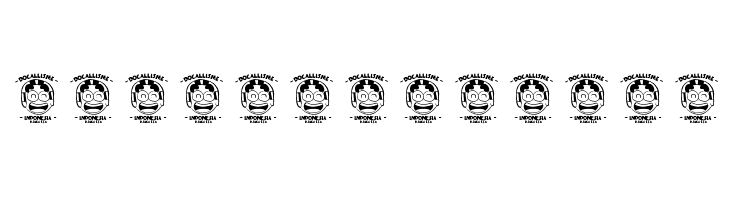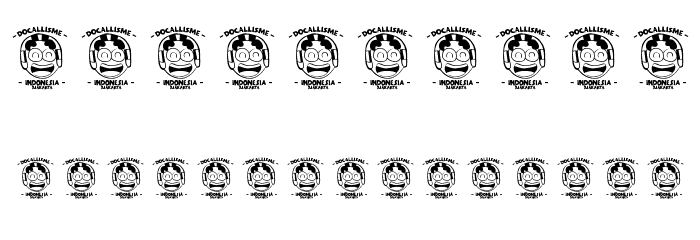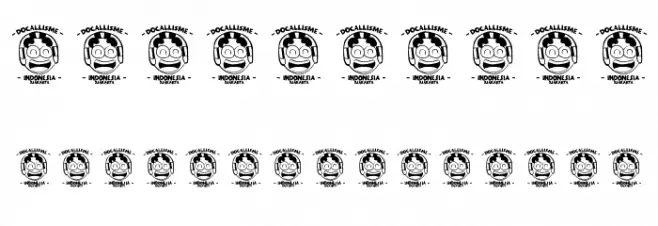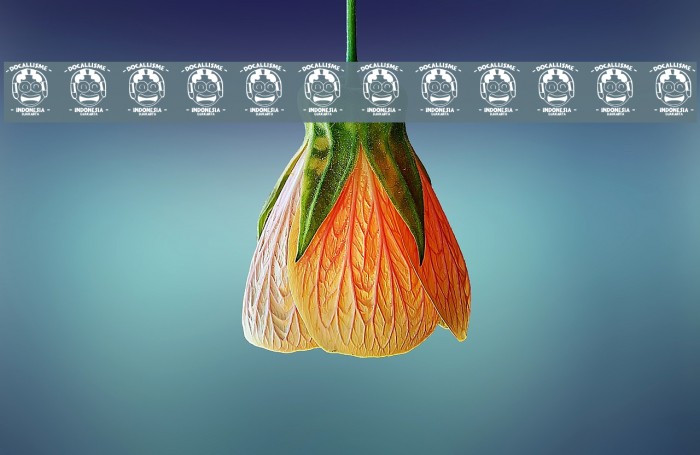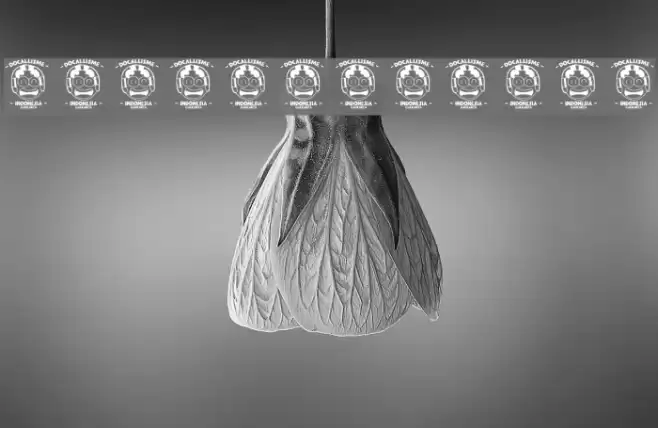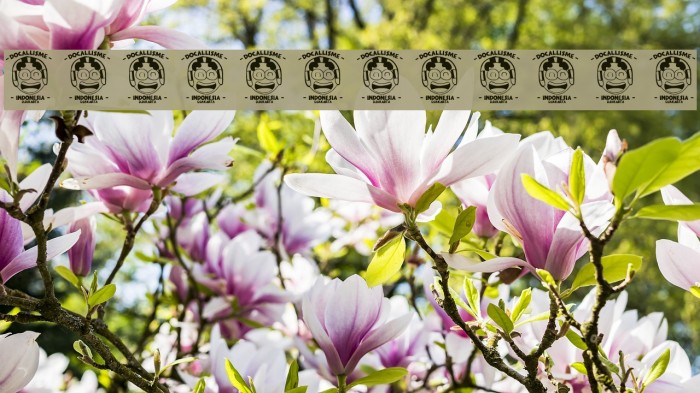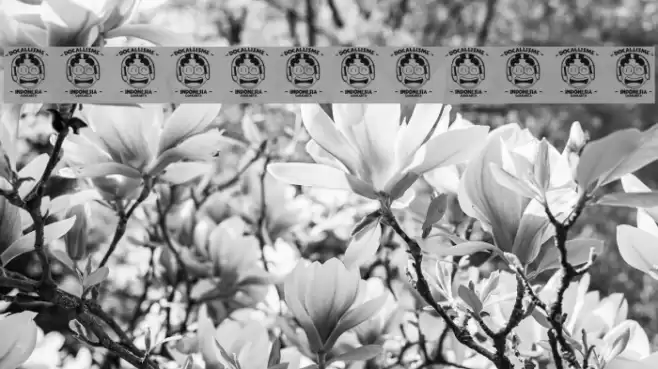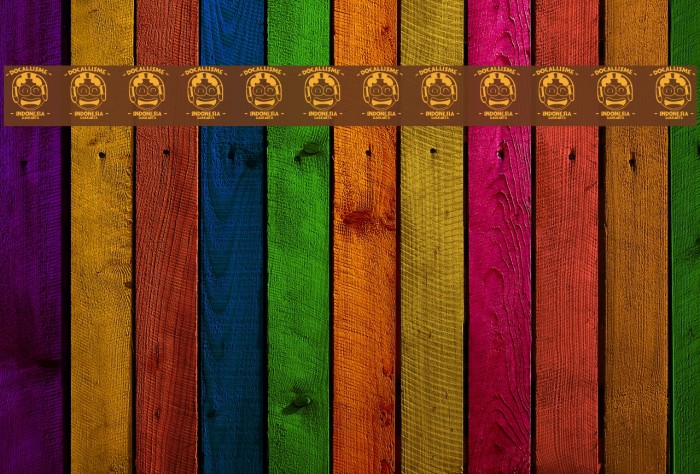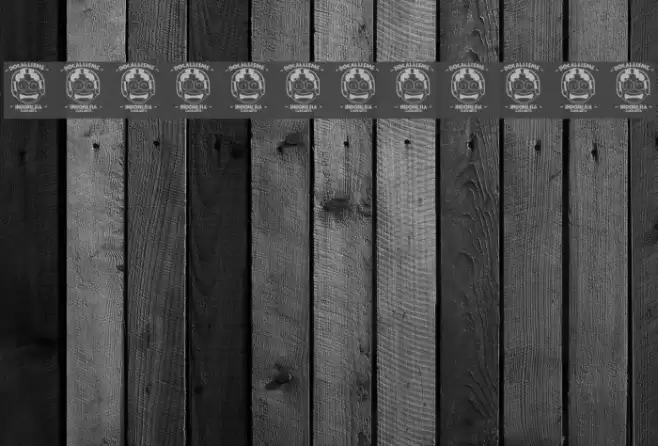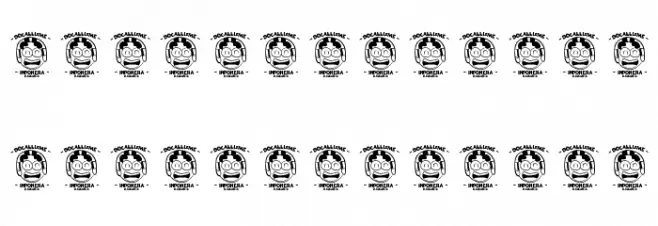
INDAH-PAPUAKU Font
| समग्र शैली | Modern, Playful |
| उपयोग का मामला | Headlines, Logos, Posters, Branding |
| सुझाए गए प्रोजेक्ट | Children's books, educational materials, branding for playful or tech companies, posters, and social media graphics. |